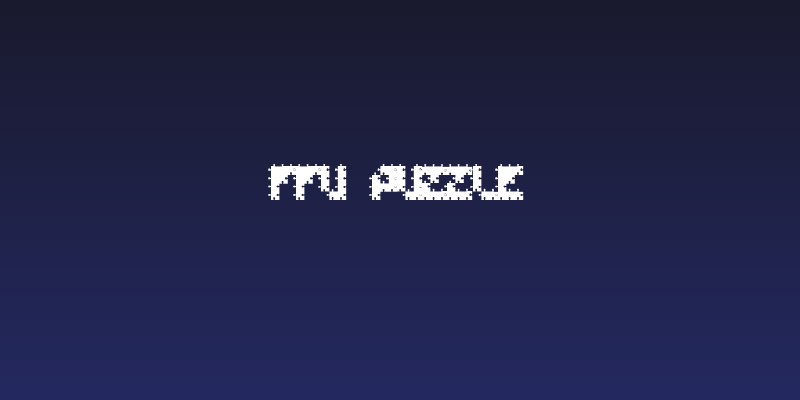
FFU Puzzle Font
| Gesamtstil | Playful, Creative |
| Vorgeschlagene Projekte | Ideal for children's books, educational materials, creative posters, and playful branding. |